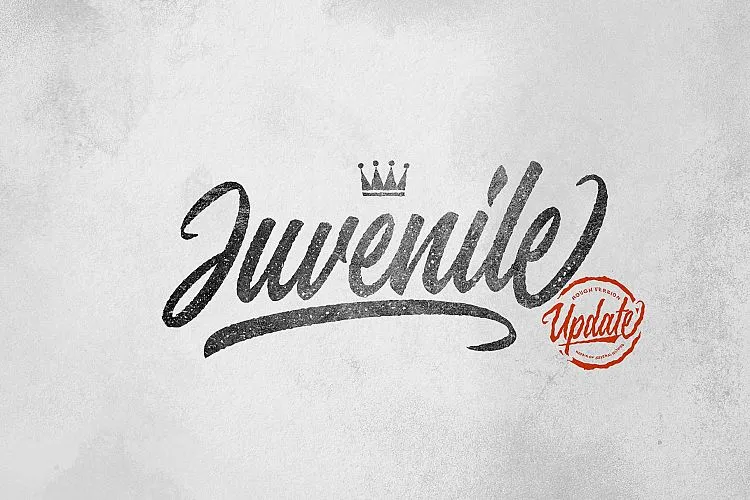
Juvenile Typeface – Download Grátis
A Juvenile Typeface é uma fonte tipográfica para estilos de letra à mão desenvolvida com amor no estilo de letras desenhadas a mão. Ela traz elementos de streetwear e vintage, criando uma experiência visual encantadora e vibrante ideal para uso em branding e logotipia. Esta elegante fonte brush style é perfeita não apenas para logos e materiais publicitários, mas também para t-shirts, embalagens de produtos, cabeçalhos, posters, cartões de aniversário e muito mais. A Juvenile inclui um conjunto completo de letras maiúsculas e minúsculas, suporte a múltiplas línguas e números, sinais de pontuação e ligaduras alternativas. Engane-se se pensa que esta fonte é apenas uma mistura casual: ela oferece profundidade e beleza que vão muito além do simples desenho à mão. Uma escolha perfeita para quem procura um toque único e vibrante em seu design gráfico.